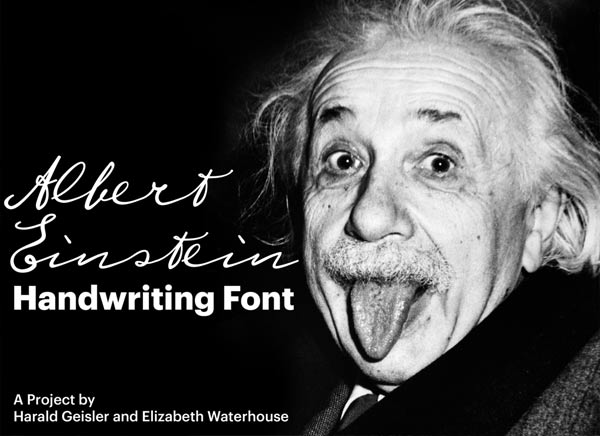
Je ne sais pas si le physicien théoricien Albert Einstein aurait apprécié cette initiative, mais ce qui est certain c’est que son écriture manuscrite est sur le point de devenir une police de caractère que les graphistes et autres infographistes vont adorer.
Un peu d’Albert
Alors que ce n’est encore qu’un projet tout juste débarqué sur Kickstarter, la police de caractère ‘Albert Einstein Font’ a été financée en quelques jours seulement et pour cause, elle reprend trait pour trait l’écriture manuscrite du célèbre chercheur allemand.
Dessinée au pixel près à partir d’authentiques écrits par le typographe allemand Harald Geisler avec Elizabeth Waterhouse sous licence Corbis – l’exploitant exclusif des marques Albert Einstein et Einstein -, cette police pour artistes et poètes devrait être disponible dès le début de l’année 2016 au prix de 40 $ environ, à condition d’apporter votre contribution ici.
Une belle typographie inspirée et inspirante ! 😉